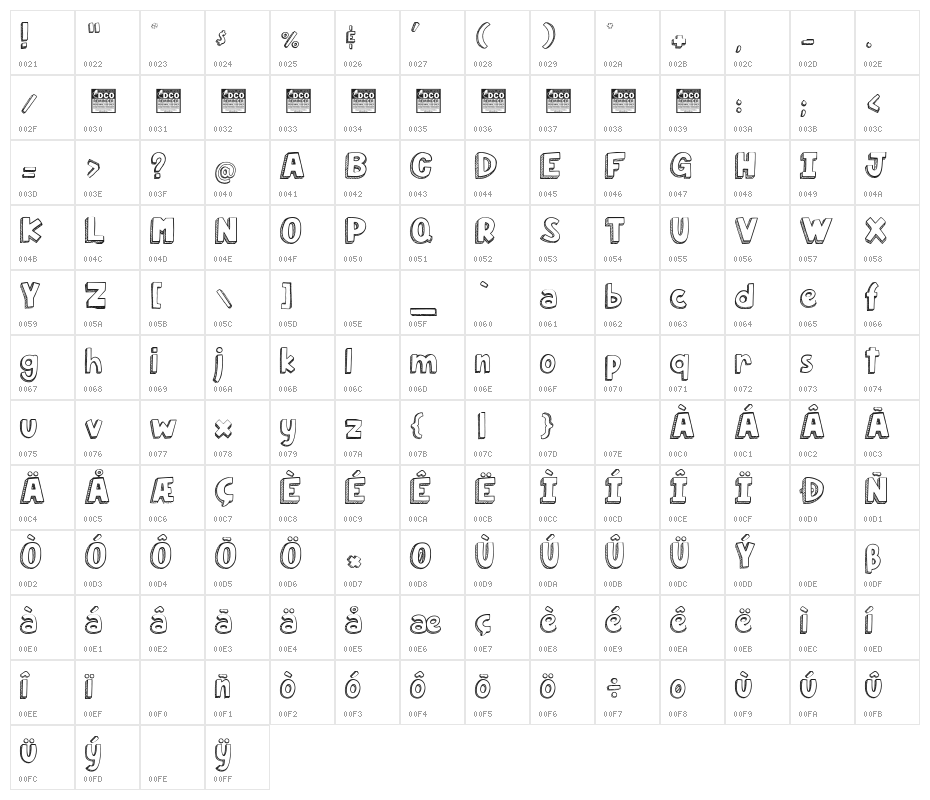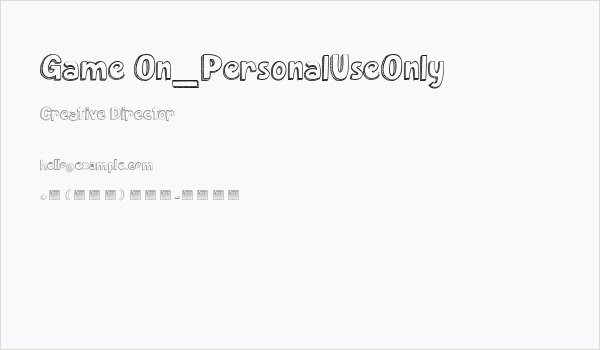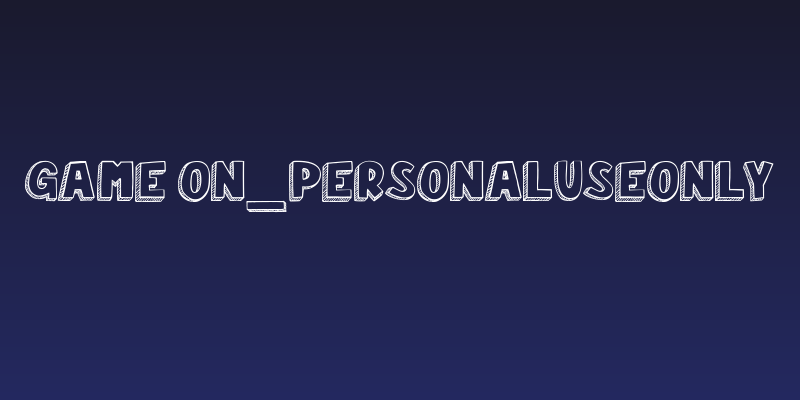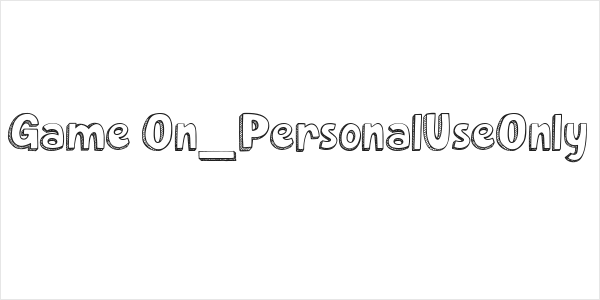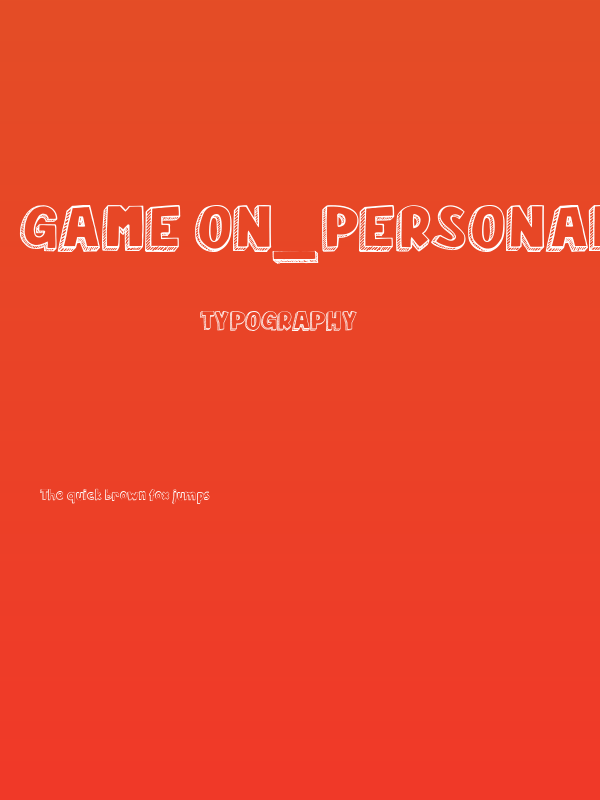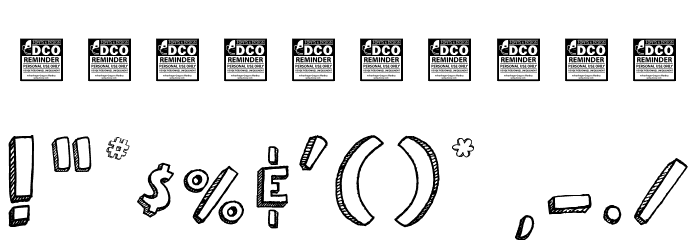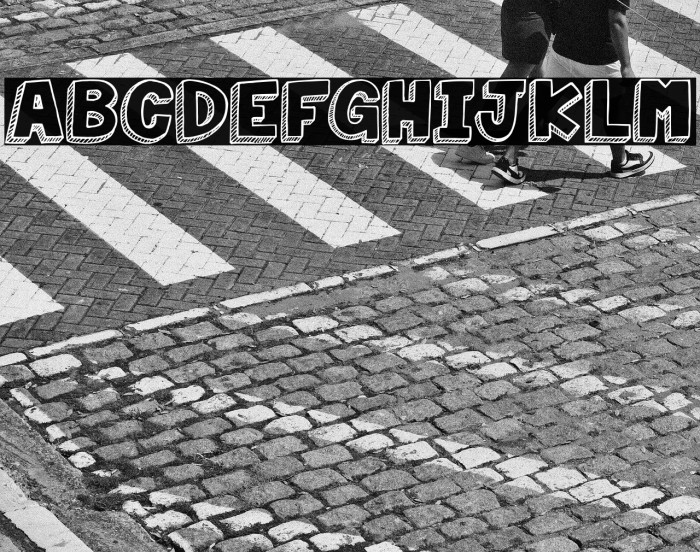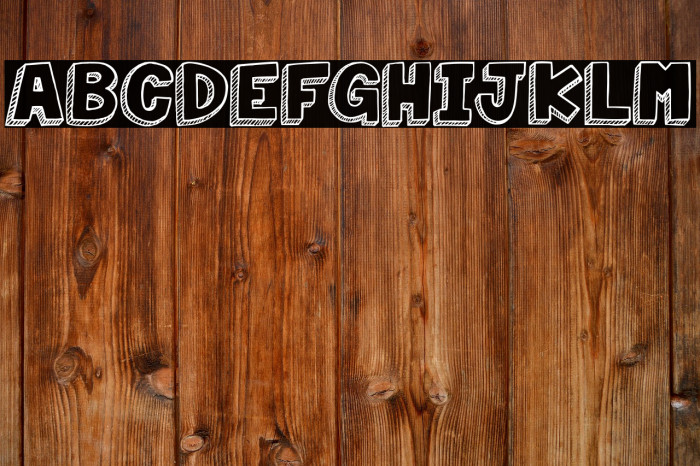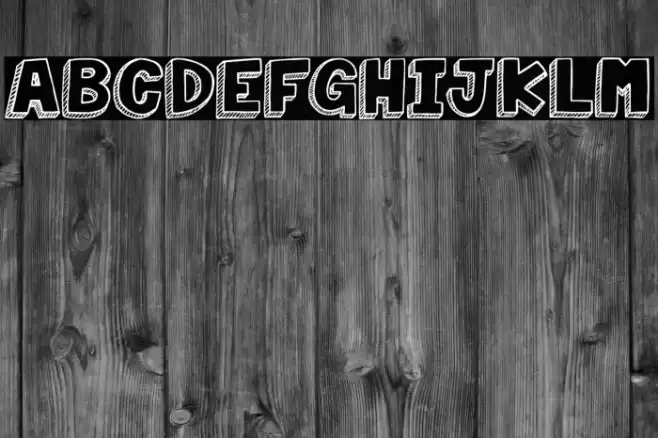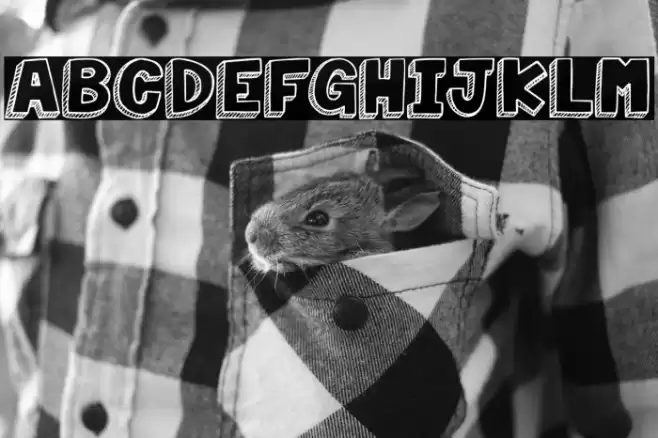
Game On_PersonalUseOnly Font
✎ Comic
Fonts by dcoxy
| Категория | Comic |
| Общий стиль | Playful, Hand-drawn |
| Область применения | Headlines, Logos, Informal Text |
| Рекомендуемые проекты | Ideal for children's books, comic strips, playful branding, and casual invitations. |